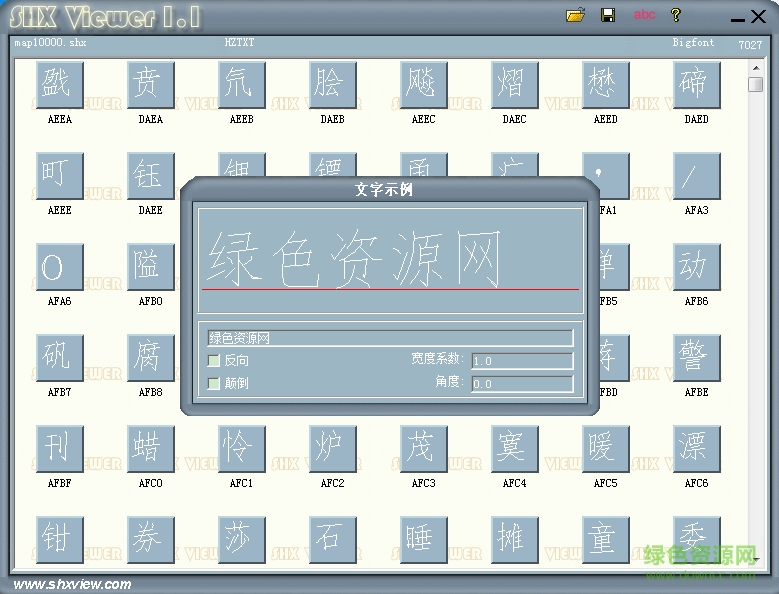
map10000.shx是一款常用的cad字體,這款字體筆畫端正大方,整體效果非常不錯,很多cad圖紙都使用了這款字體,喜歡的朋友歡迎來綠色資源網免費下載使用。
shx字體文件,是一種用矢量描述的形文件,shx專門的中文字庫,這種字庫的文件擴展名為.SHX,autocad中用戶可自己定義擴展名為 “ .shp”形定義字體文件。